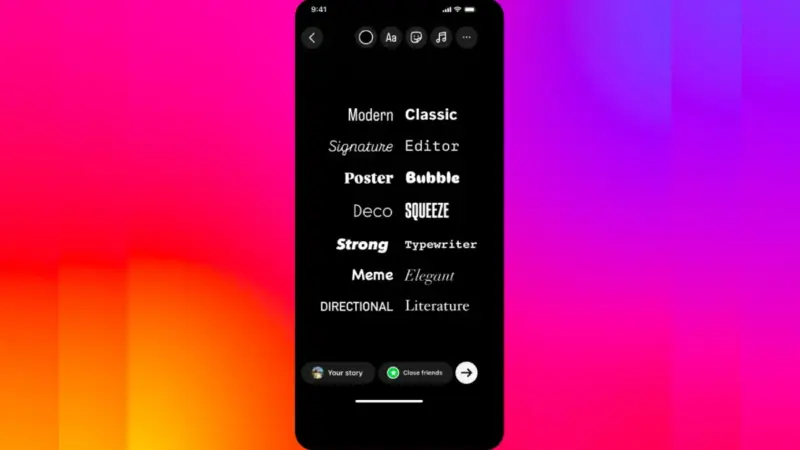
Instagram, kullanıcıların kendilerini ifade edebilecekleri en popüler sosyal medya platformlarından biri. Profil açıklamaları, gönderi başlıkları, hikayeler ve yorumlar aracılığıyla hem bireysel kullanıcılar hem de markalar, kendi tarzlarını ortaya koymak ister. Bu noktada, Instagram yazı tipi değiştirme işlemi öne çıkar. Çünkü farklı yazı tipleriyle yapılan paylaşımlar, standart metinlerden ayrılır ve dikkat çeker. Peki, Instagram yazı tipi nasıl değiştirilir? Hangi araçlar kullanılır ve dikkat edilmesi gerekenler nelerdir? İşte adım adım rehber.
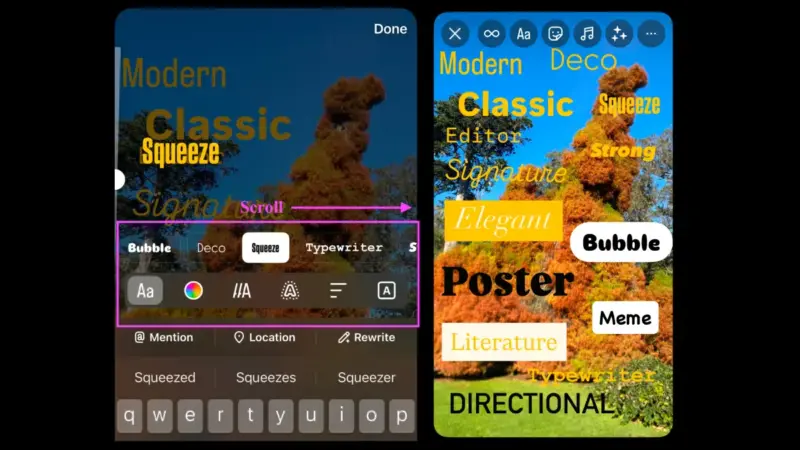
Instagram Yazı Tipi Değiştirme Neden Önemlidir?
Instagram’da öne çıkmak için sadece görsel paylaşmak yetmez; metinlerinizin de dikkat çekici olması gerekir. Yazı tipi değiştirerek:
- Profilinizin benzersiz görünmesini sağlayabilirsiniz.
- Gönderi ve hikaye içeriklerinizde yaratıcı bir etki oluşturabilirsiniz.
- Markanızın veya kişisel stilinizin farklılığını ortaya koyabilirsiniz.
- Takipçilerinizin dikkatini daha fazla çekebilir, etkileşim oranınızı artırabilirsiniz.
Instagram Yazı Tipi Nerelerde Değiştirilebilir?
Instagram yazı tipi değiştirme işlemi, aşağıdaki alanlarda kullanılabilir:
- Biyografi (bio) kısmında
- Gönderi açıklamalarında
- Yorumlarda
- Hikaye yazılarında
- IGTV veya Reels başlıklarında
Instagram Yazı Tipi Değiştirme Nasıl Yapılır?
Instagram’ın kendisinde sınırlı yazı tipi seçeneği vardır. Özellikle hikayelerde birkaç farklı stil sunulsa da, gönderilerde ve biyografi kısmında özel font seçimi yapılmaz. Ancak üçüncü taraf araçlar sayesinde bu değişiklikleri kolayca yapabilirsiniz.
Yazı Tipi Dönüştürücü Siteleri Kullanmak
Aşağıdaki siteleri kullanarak istediğiniz yazıyı farklı fontlarda oluşturabilir ve Instagram’a yapıştırabilirsiniz:
Popüler Yazı Tipi Dönüştürücüler:
Kullanımı:
- Siteye girin.
- Yazmak istediğiniz metni kutuya yazın.
- Aşağıda otomatik olarak farklı yazı tipleri görüntülenecek.
- Beğendiğiniz fontu kopyalayın.
- Instagram uygulamasına girin ve ilgili alana yapıştırın.
Mobil Uygulamalar Kullanmak
Android ve iOS cihazlar için kullanılabilecek bazı popüler yazı tipi uygulamaları şunlardır:
- Fonts (iOS ve Android)
- Fontify
- Stylish Text
- Cool Fonts
Bu uygulamalar, farklı yazı tiplerinde metin yazmanızı sağlar ve kopyalayıp Instagram’a yapıştırmanıza olanak tanır.
Hikayelerde Yazı Tipi Nasıl Değiştirilir?
Instagram hikaye özelliği içinde doğrudan yazı tipi değiştirebilirsiniz.
Adımlar:
- Hikaye oluşturmak için Instagram’ı açın.
- Fotoğraf veya video ekleyin.
- Yazmak istediğiniz metni girin.
- Ekranın üst kısmında yer alan “Aa” ikonuna dokunun.
- Sağ alt köşedeki yazı tipi seçeneklerini kaydırarak farklı stilleri deneyin.
- Renk ve hizalama gibi diğer ayarları da yaptıktan sonra paylaşabilirsiniz.
Profil Biyografisinde Yazı Tipi Değiştirme
Profil biyografiniz (bio), bir kullanıcının sizi ziyaret ettiğinde gördüğü ilk şeylerden biridir. Bu yüzden yazı tipiniz burada fark yaratabilir.
Örnek:
🅷🅴🅻🅻🅾, 𝑊𝑒𝑙𝑐𝑜𝑚𝑒 𝑡𝑜 𝑚𝑦 𝑝𝑟𝑜𝑓𝑖𝑙𝑒!
Yazı tipini değiştirmek için yine yazı tipi dönüştürücü sitelerden birini kullanarak metninizi oluşturup profilinize yapıştırmanız yeterli.
Dikkat Edilmesi Gerekenler
Instagram yazı tipi değiştirme işlemi faydalı olsa da, bazı noktalara dikkat etmeniz gerekir:
- Okunabilirlik: Bazı yazı tipleri çok süslü olabilir ve okunması zorlaşabilir. Takipçilerinizin rahatça okuyabileceği stilleri tercih edin.
- Fazla karmaşa: Her cümlede farklı yazı tipi kullanmak görsel olarak kafa karıştırıcı olabilir. Tutarlı bir stil tercih etmek daha profesyonel görünür.
- Uyumluluk sorunları: Bazı özel yazı tipleri eski cihazlarda veya bazı tarayıcılarda görünmeyebilir.
- Spam gibi görünmemek: Aşırı dikkat çekici ve abartılı yazı tipleri, bazı kullanıcılar tarafından spam olarak algılanabilir. Özellikle markalar için sade ama şık yazı tipleri tercih edilmelidir.
Yazı Tipi Değiştirmenin Instagram’daki Etkisi
Yazı tipi değişikliği, profilinize veya paylaşımlarınıza küçük ama etkili bir dokunuş katabilir. Özgünlük, Instagram’da fark edilmenin anahtarıdır ve bu tür küçük detaylar markalaşma sürecinde bile önemli farklar yaratabilir. Özellikle influencer’lar, butik işletmeler veya içerik üreticileri için bu tarz görsel detaylar etkileşimi artırmada etkili olur.
Instagram yazı tipi değiştirme, basit ama etkili bir yöntemdir. Profilinize özgünlük katmak, gönderilerinizi daha dikkat çekici hale getirmek ve takipçilerinizle yaratıcı bir şekilde etkileşime geçmek için farklı yazı tiplerini deneyebilirsiniz. Doğru araçları kullanarak, sadece birkaç adımda Instagram’da daha profesyonel ve estetik bir görünüm elde etmek mümkün.
Unutmayın: Yazı tipi sadece bir görsel öğe değil, aynı zamanda kimliğinizin bir yansımasıdır.